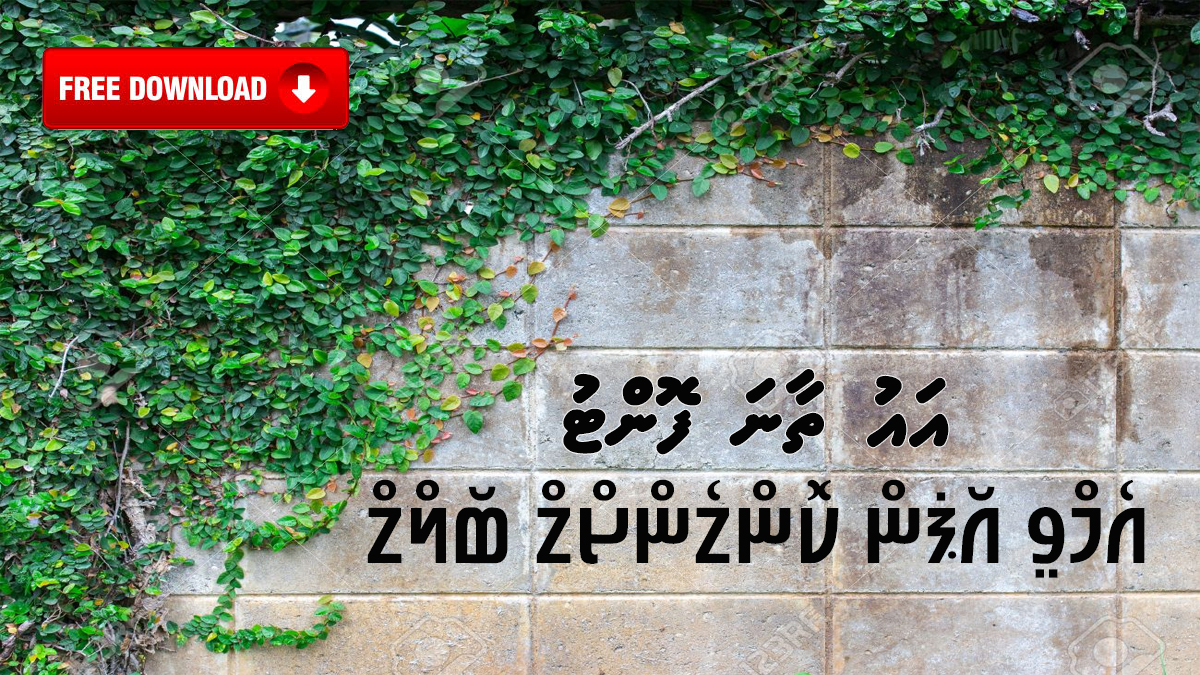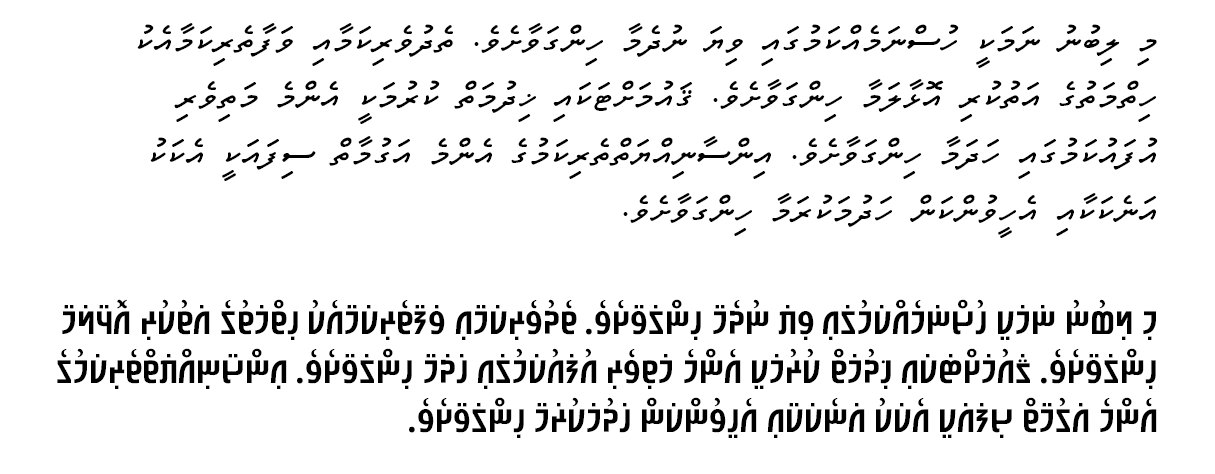
އެމްވީ އޯޕަން ކޮންޑެންސްޑް ބޯލްޑް (އެމްވީ އޯޕަން ހަނި ފަލަ)
ތާނަ ލިޔާއިރު، ބައެއް ފަހަރު ހަނި، ޖާގަނެތް ތަންތަނުގައި ފަލަ ސުރުޚީތައް ލިޔަން ޖެހެއެވެ. މިފަދަ ޙާލަތްތަކަށް ބޭނުންވަނީ ދިގުކޮށް ހަނިކޮށް ހުންނަ އަކުރުތަކެއް ހިމެނޭ ފޮންޓެކެވެ. މިފަދަ އިނގިރޭސި ފޮންޓުތައް އޮންލައިން ނޫސްތަކުގައި ސުރުޚީލިޔުމަށާއި މިނޫނަސް ޖާގަ ހަނިތަންތަނުގައި ތަކެތި ލިޔުމަށް ބޭނުން ކުރެއެވެ.
ތާނަ ޢާއްމުކޮށް ލިޔަނީ ރަހައިން 30 ދަރަޖައަށް މައްޗަށް ކަތިކޮށެވެ. މިއީ ވަރަށް ބޮޑު ކަތި މިންވަރެކެވެ. ޢާއްމުކޮށް އިނގިރޭސި އަކުރުތައް ކަތިކުރަނީ މިހާރަކަށް އައިސް 81 ދަރަޖަ އާއި 84 ދަރަޖައާ ދެމެދަށެވެ. އެހެން ގޮތަކަށް ބުނާނަމަ، ކަތިމިން ހުންނާނީ އޮލަނބަށް ވުރެ 6 ދަރަޖައާއި 9 ދަރަޖައާ ދެމެދުގައެވެ. ގާތްގަޑަކަށް ތެދަށެވެ. އަކުރުތަކެއް ކަތިވި ވަރަކަށް ކިޔަން ދަތިކަމަށް ދިރާސާތަކުން ދައްކައެވެ. ޢާއްމުކޮށް އަކުރުތައް އެންމެ ކަތިކޮށް ލިޔަނީ ތާނައިގައެވެ. އަކުރުތައް ޢާއްމުކޮށް ކަތިކޮށް ހުންނަ މިނަށް ބަލާއިރު ތާނައަކީ ދުނިޔޭގެ ރެކޯޑެވެ. މިކަމުގެ ނަތީޖާއަކީ ތާނަ އަވަހަށް ކިޔަން ދަތިވުމެވެ. އެހެން މެދުވެރިވަނީ އިންސާނާގެ ލޮލުގެ އެތެރޭގައި ސެލްތައް އެތުރިފައި ހުންނަ ގޮތުންނެވެ.
ނަމަވެސް ތާނައަކީ ހުރިހާ ވޭލައަކު މިހާ ކަތިކޮށް ލިޔުނު އަކުރުތަކެއް ނޫނެވެ. ކުރީ ޒަމާނުގެ ލިޔުންތަކުގައި ތާނަ އަކުރުތައް ހުންނަނީ ތެދަށެވެ. އަކުރުތައް ކަތިކޮށް ލިޔެވެން ފެށީ މީގެ 200 ވަރަކަށް އަހަރު ކުރިންނެވެ. ކުރީގެ އަކުރުތައް މިހާރުގެ އަކުރުތަކަށް ވުރެ ތެދުބޮޑުވެފައި ކިޔަން ފަސޭހަވާނެއެވެ.
މިފަހަރު ތިޔަ ބޭފުޅުންނަށް މިހުށަހަޅާ ފޮންޓަކީ ގޫގުލް ފޮންޓެއް ކަމުގައިވާ އޯޕަން ސާންސް ކޮންޑެންސްޑް އަކުރުތަކާ އެކުމުތުވާ (ހާމަނައިޒްވާ) ގޮތަށް ފަރުމާކޮށްފައިވާ ފޮންޓެކެވެ. މިފޮންޓުގައި ތާނައަކުރުތައް ހުންނާނީ މުޅިންހެން ތެދަށެވެ. ދިގުމިނަށް ވުރެ ފުޅާމިން ހަނިކޮށެވެ. ބައެއް ކަހަލަ ބޭނުންތަކަށް މިއަކުރުތައް ވެސް ބަޔަކަށް ކަމުދާނެ ކަމަށް ހީކުރަމެވެ. އަކުރުތަކުގެ ނަމަށް އެމްވީ އިތުރުކުރީ މި ފޮންޓު ކޮމްޕިއުޓަރުން ހޯދަން ފަސޭހަ ކުރުމަށެވެ.
ތިރީގައިވާ ސާމްޕްލްގެ ދެ ޕެރެގުރާފު ލިޔެފައިވަނީ އެއް ސައިޒަކުންނެވެ.
އަޅުގަނޑުގެ ކުރީ މަޒުމޫނުތަކުގައި ތާނަލިޔުމަށް ގެނެވިދާނޭ ބައެއް ކުރިއެރުންތައް ބަޔާންކޮށްފައިވާނެއެވެ. އެއިން އެއް ކަމެއް މިފޮންޓުގައި ހިމެނެއެވެ. އެއީ އަބަފިލި ކުރުކޮށް ތިއްކެއްގެ ގޮތުގައި ޖެހުމާއި އާބާފިލި ދެތިކީގެ ގޮތުގައި ޖެހުމެވެ. އިބިފިއްޔާއި އީބީފިއްޔަށް ވެސް މި ބަދަލު ގެނެސްފައި ވާނެއެވެ. ތިކިޖެހި އަކުރުތައް ލިޔާއިރު މި ފިލިތަކާ އޮޅިދާނެތީ އަކުރުތަކުގެ ފިލިތައް މި ފޮންޓުގައި ހިމެނޭނީ ޢާއްމު އަކުރަކަށް ވުރެ މަތި ނުވަތަ ތިރި ނުވާނޭ ގޮތަށެވެ. އެނގިވަޑައިގަންނަވާނޭ ފަދައިން އެވޭލާ އަކުރުން ދިވެހި ލިޔާއިރު، އަބަފިއްޔެއް ނުޖަހައެވެ. ފިލިނުވާނަމަ، ބަލަނީ އަބަފިލި ކަމަށެވެ. މިއީ ދެކުނު އޭޝިޔާގެ ބަސްލިޔާ ގިނަ އަކުރުތަކުގެ ސިފައެކެވެ.
Very unique and aesthetically appealing, but has similarities to Mishnaic and other classic Hebrew writing though. To have a, aa, i, ee being two pixels wide might make it more reader-friendly, by better distinguishing them from the nukuhtaa.
Hassan keevvethoa abafili aabaa fili thedhah nuliyuvvee. Athireegey thaanayaa fili vaththaru vedhaanetheethoa. Ekamaku akuru thakugai ebahuri eyaa vaththauvaa gotheh. Alhugandah feney abafili ibifilives dash inna kahala rongu fiyyah badhalu kollavva . Eyrun kiyan maa faseyha vaane. Thi vidhaalhuvi gothah vaguthu bellevee vaguthu ballavaigenthoa
Kiyan faseyha ee mi article liyefa in font. Alah tha’aaraf kuri font in liyuneema kiyan v udhagoo.. Hama enme fakkalee faruma font..
As noted in the article, the font is not intended for bodytext. Only headings and titles in large sizes.